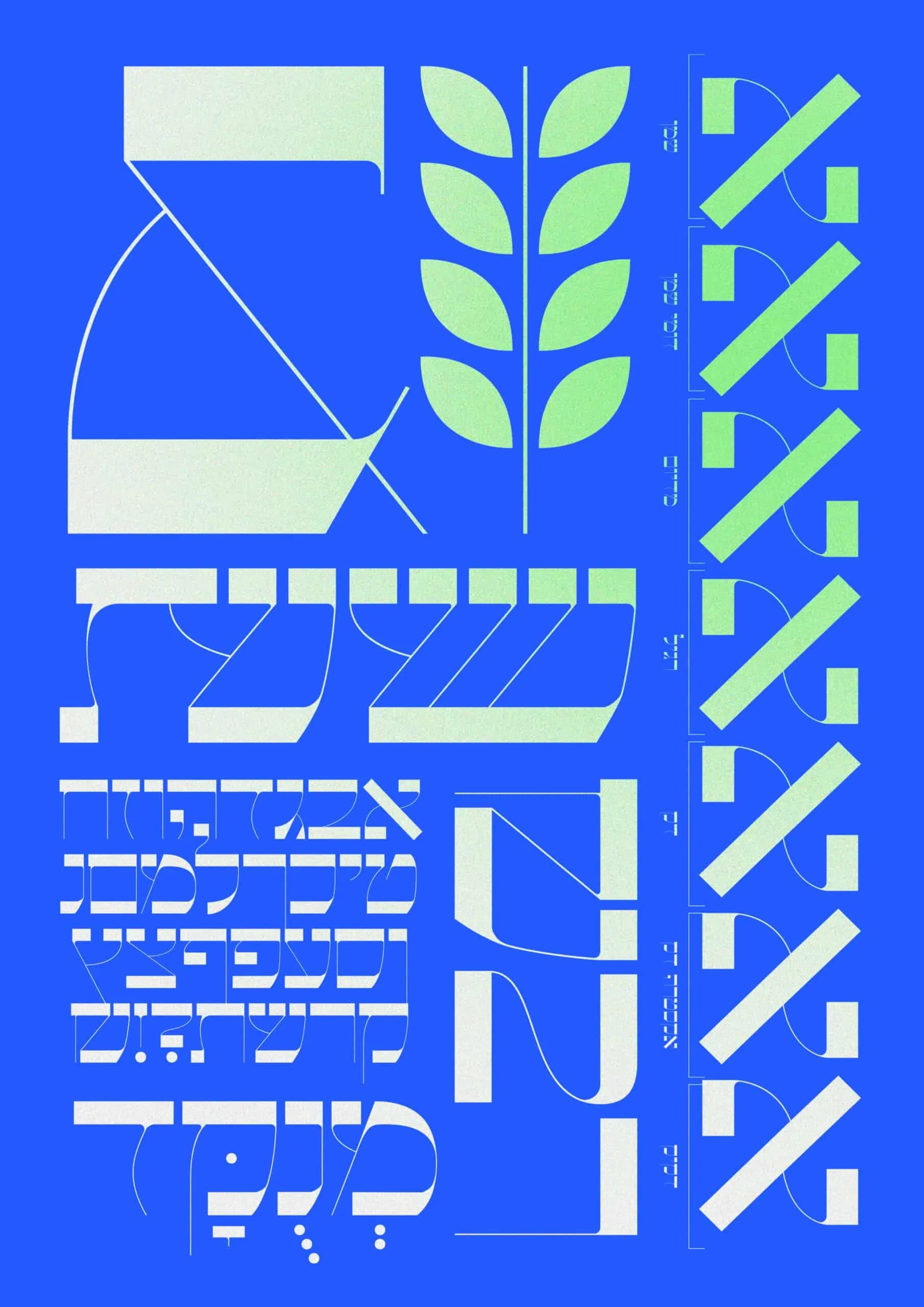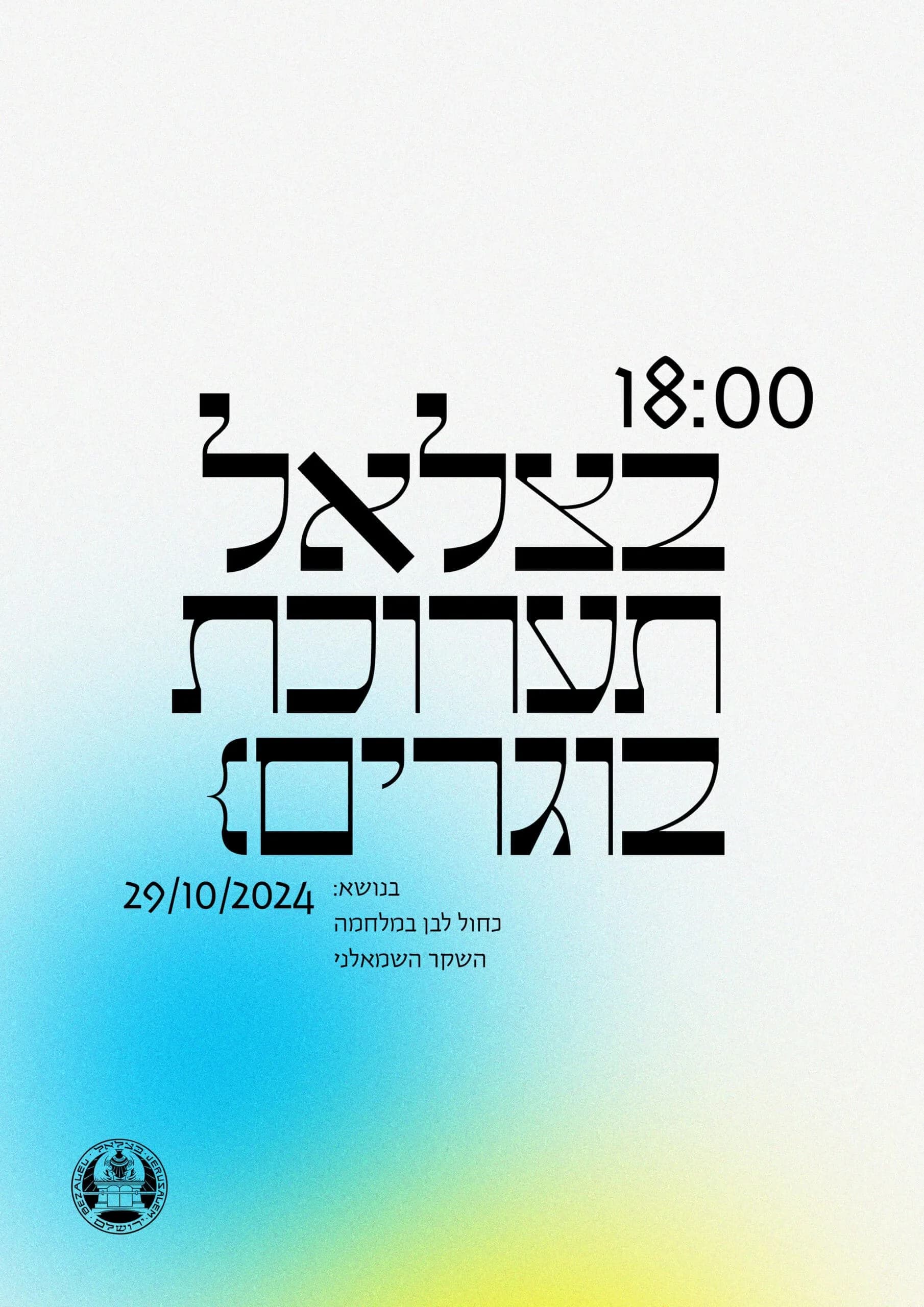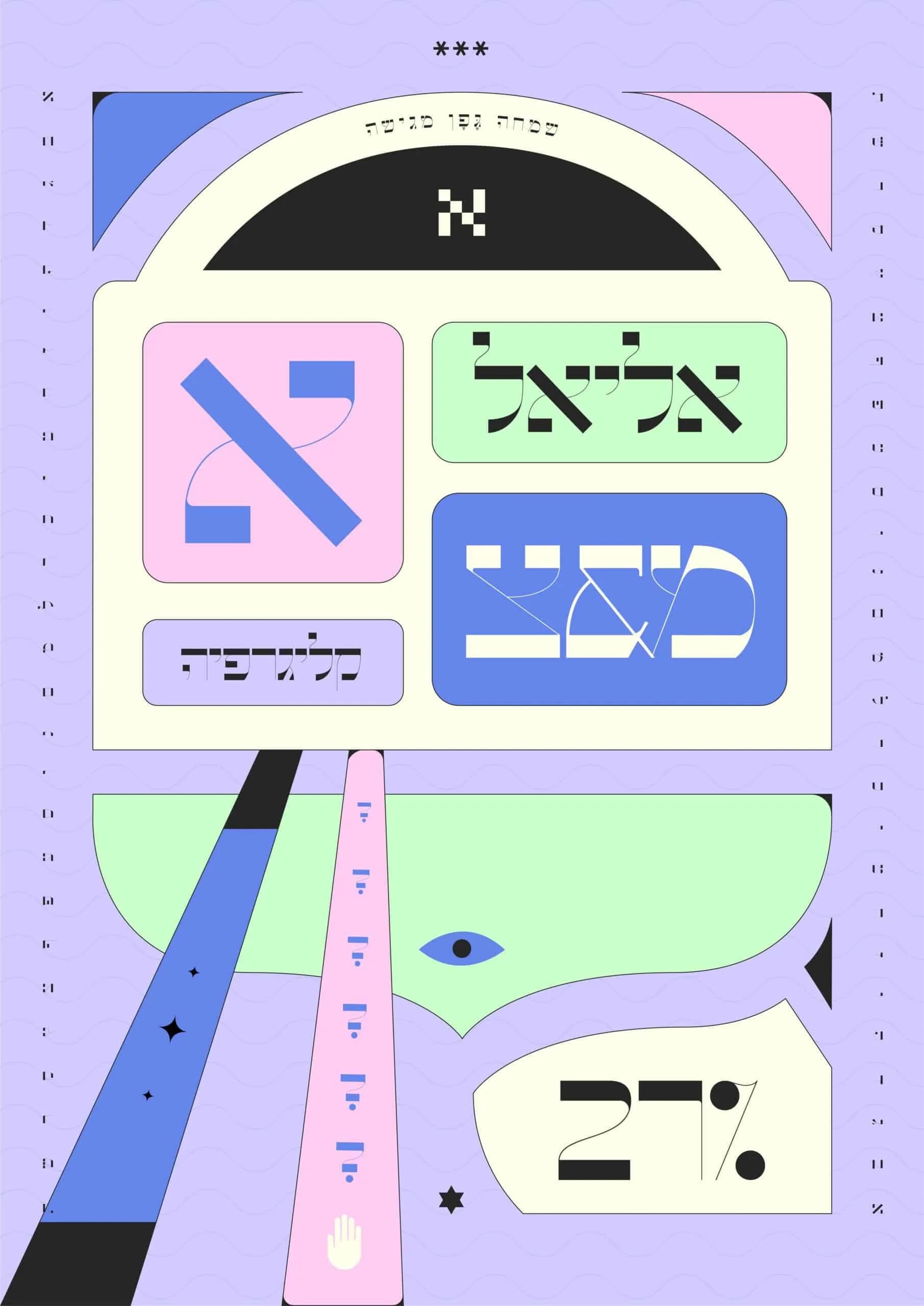
אליאל - פונט כותרות עברי עכשווי. פונט אליאל עוצב בהשראת חקירה צורנית של אותיות עבריות, תוך דיאלוג בין מודרניזם גיאומטרי לבין מוטיבים מסורתיים וקליגרפיים. הוא שואב השראה מכתב ספרות קדום אך מתעצב בשפה עיצובית חדשנית, חדה ומופשטת. הפונט משלב בין הדיוק של רישומי אדריכלות לבין הגמישות האורגנית של קליגרפיה חופשית, מה שמעניק לו אופי טקסי, אלגנטי ועוצמתי. לכל אות יש נוכחות גרפית מובהקת, והפונט כולו יוצר תחושה של מבנה, משקל וסמליות. שימושים מומלצים: תערוכות אמנות, כותרות עיצוביות, מיתוגים תרבותיים וזהות חזותית מוסדית, מושלם לפרויקטים העוסקים בישראליות, זהות יהודית, זיכרון, מקום וקדושה. אליאל מתאים למעצבים שמחפשים לשלב תחכום צורני עם עומק רעיוני, ומציע שפה עברית עיצובית חזקה, חדשה ונועזת.